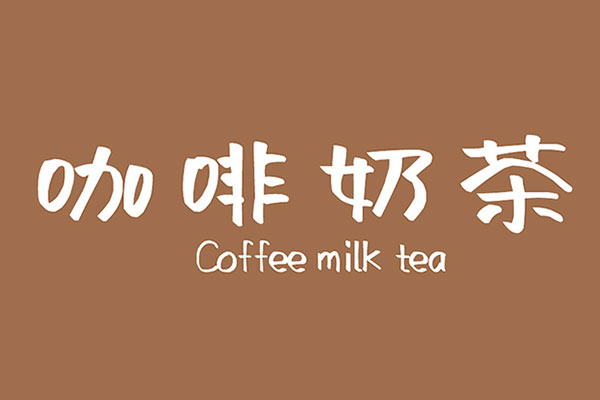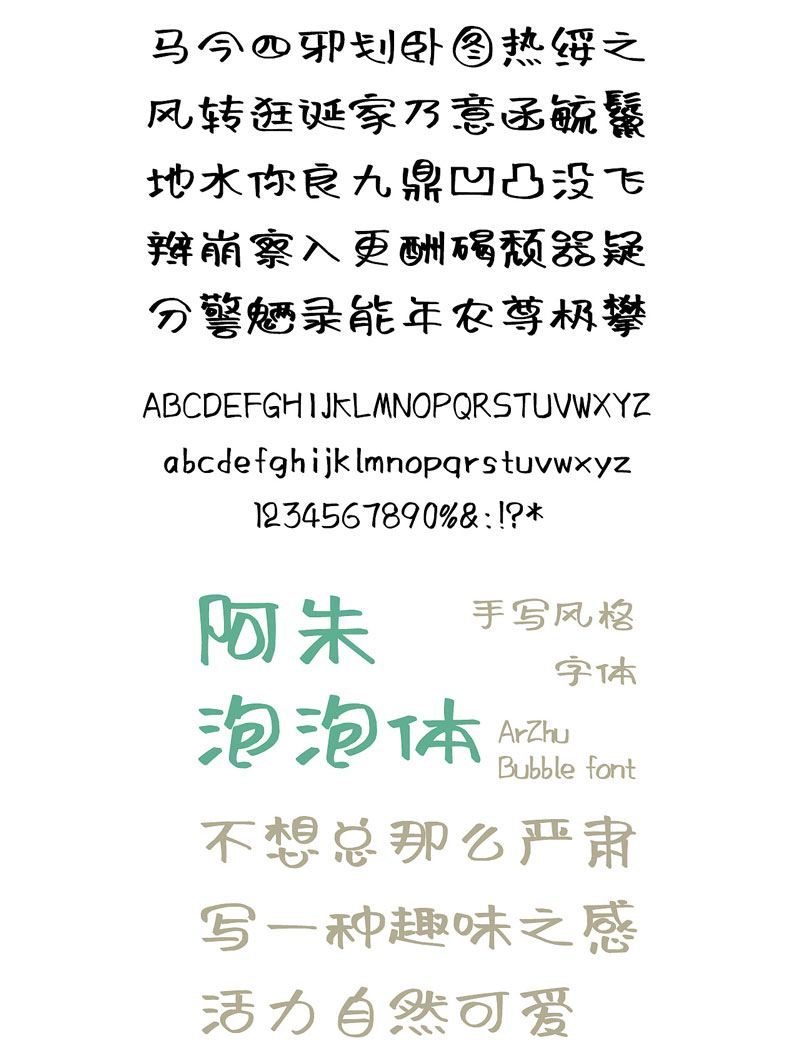
阿朱泡泡体
阿朱泡泡体,一款在2019年光棍节发布的独特字体,展现出随性、轻松的书写风格,变化丰富,充满卡通趣味和强烈的装饰色彩。这种独特的字体风格主要体现在其口型偏旁,它们是由“泡泡”形状组成的,使字体散发出一种充满青春活力的气息,其风格鲜明,特征显著。
阿朱泡泡体基于GB2312-80字符集标准,共收录了6763个常用汉字以及数百个符号。这意味着,无论是进行中文文本设计还是其他相关的创意设计,阿朱泡泡体都能为您的作品增添独特的视觉效果,使您的设计更具吸引力和创新性。
阿朱泡泡体字体效果预览